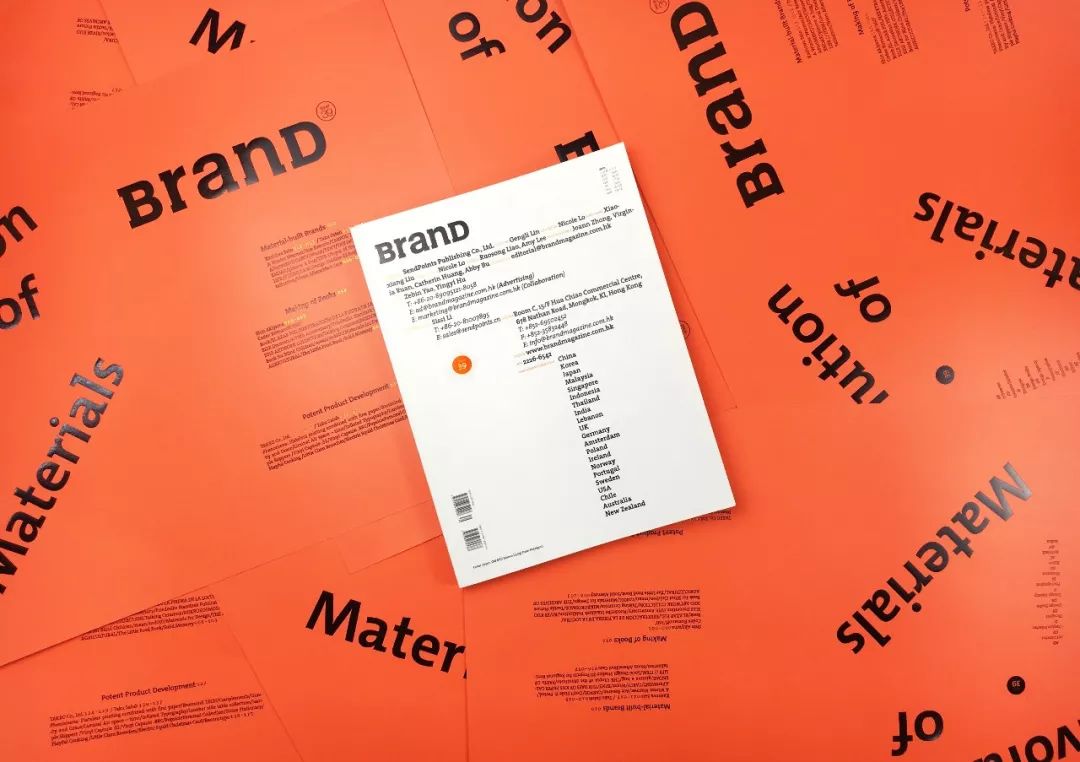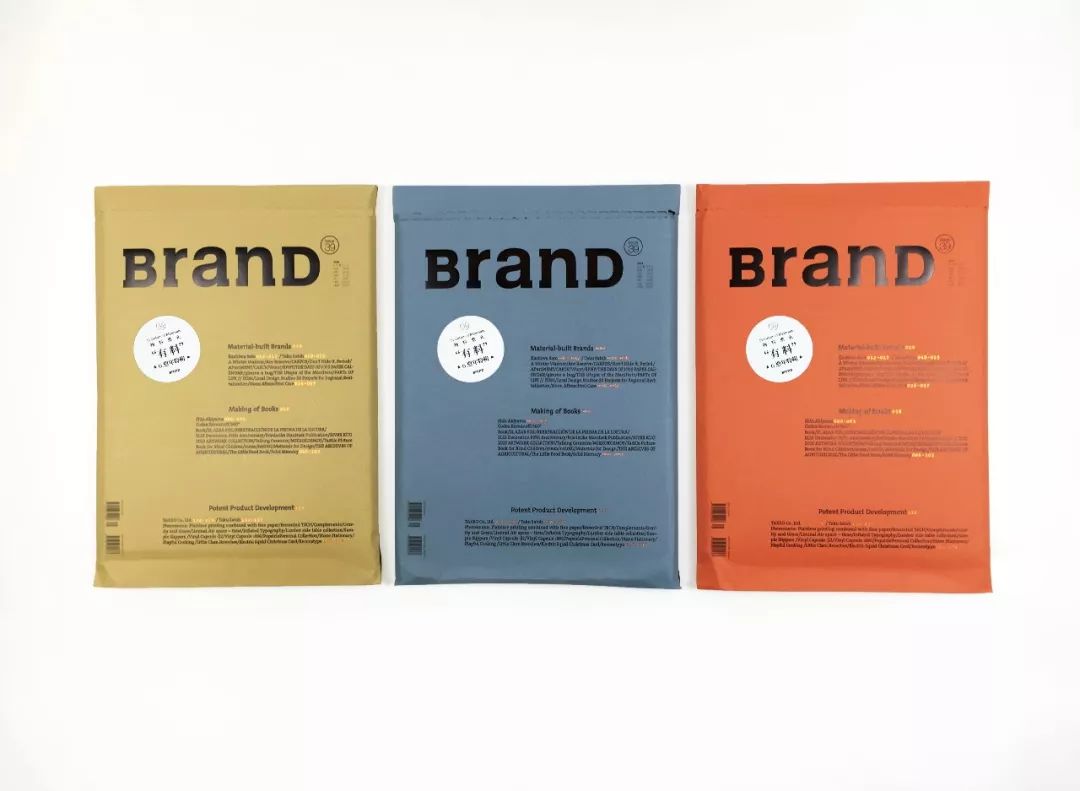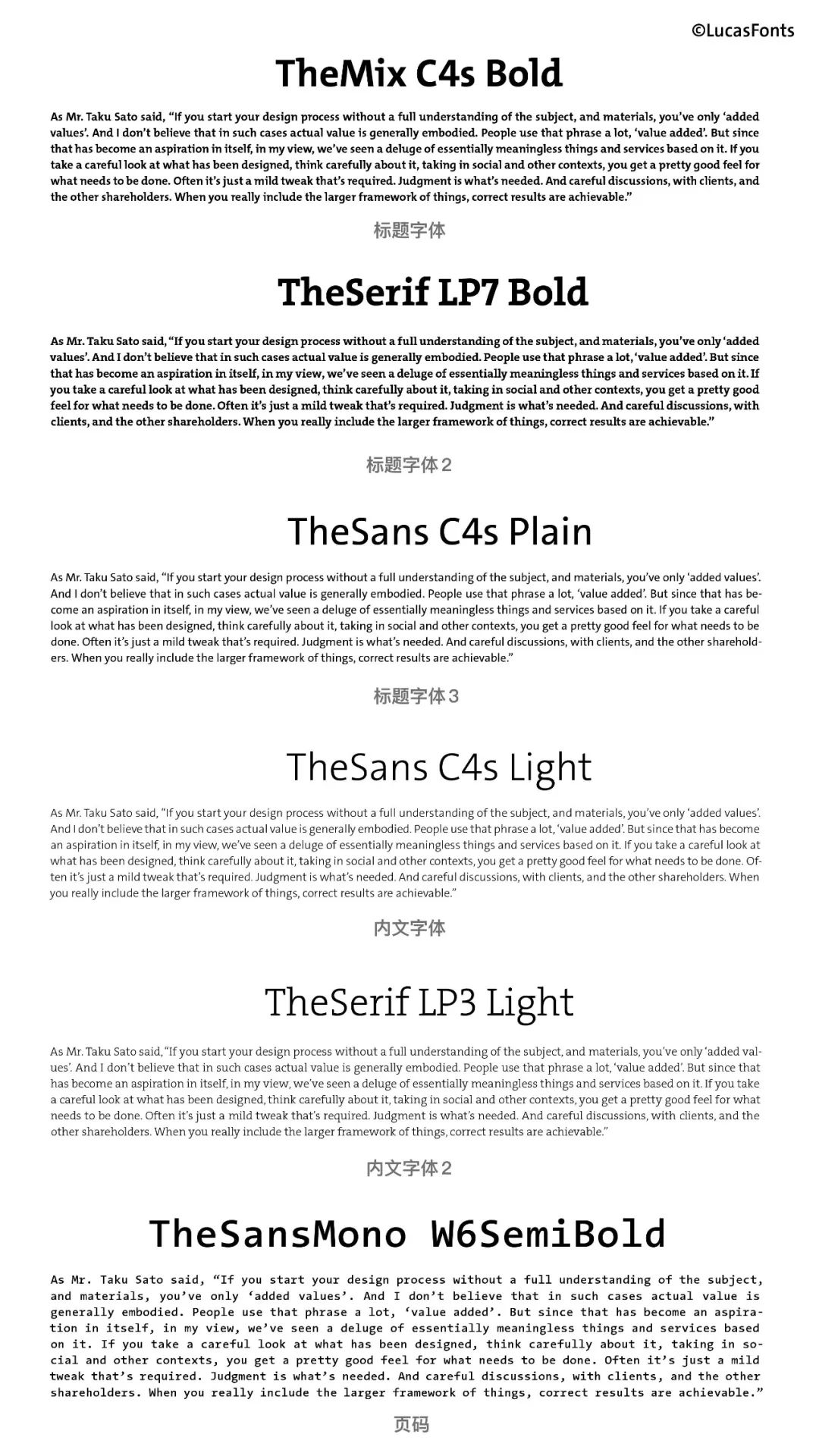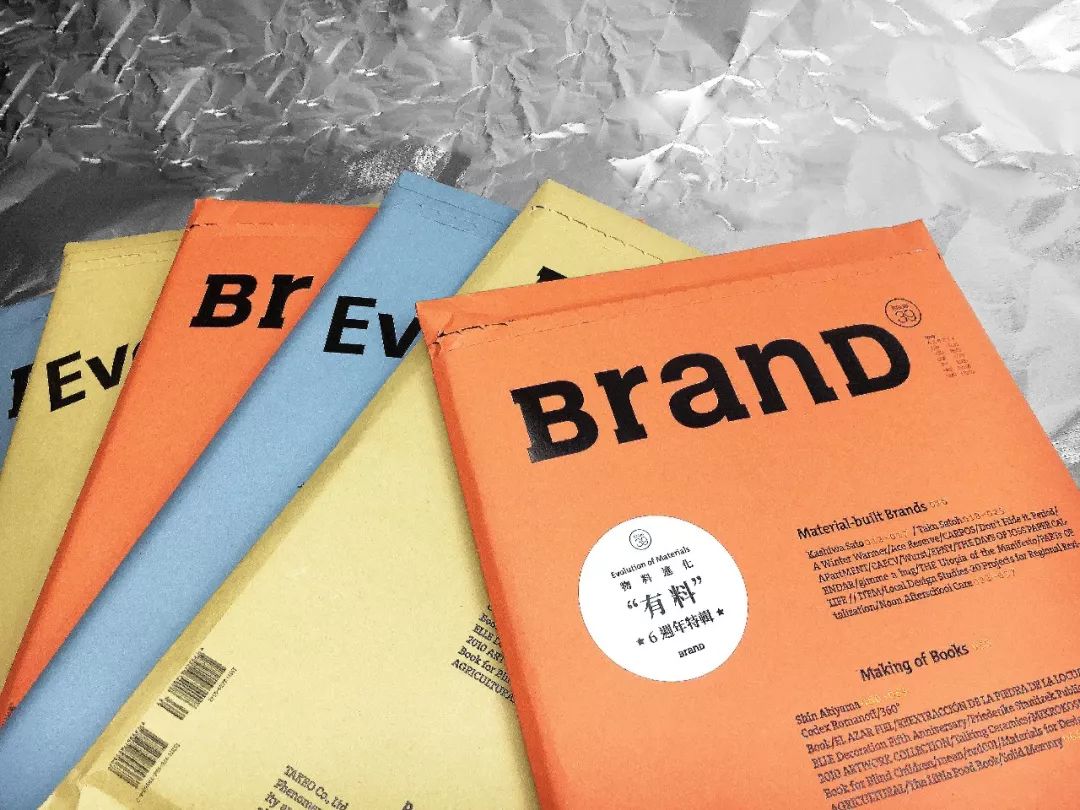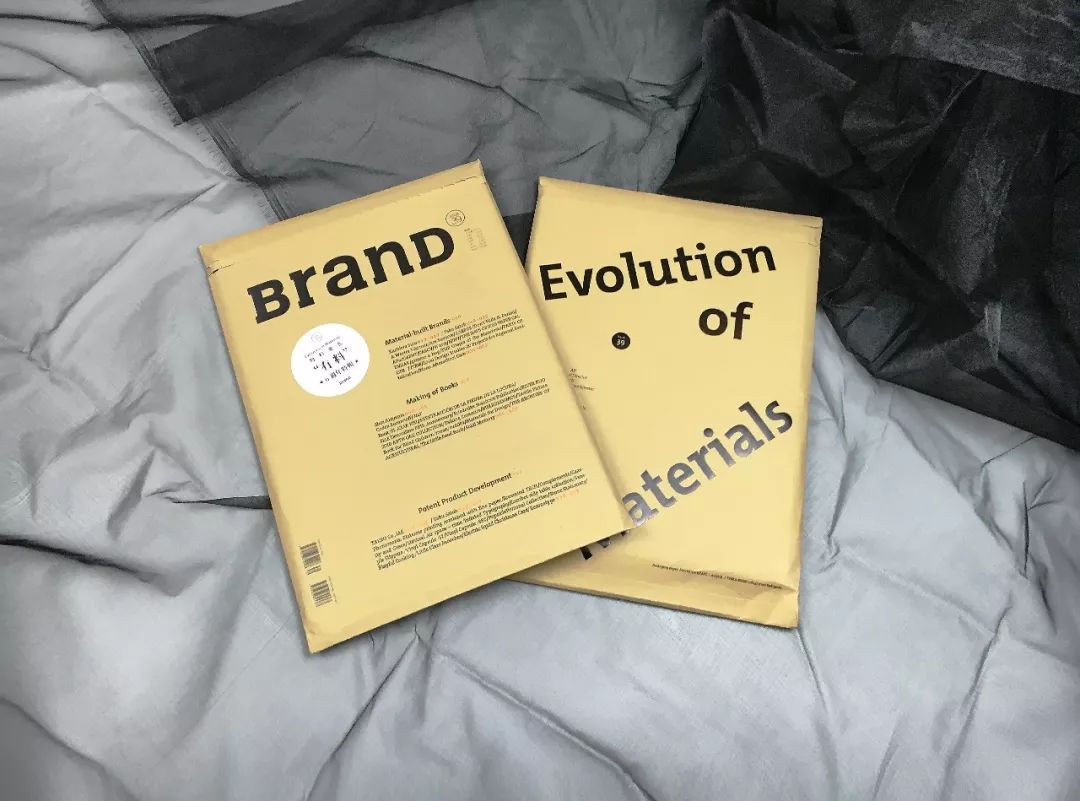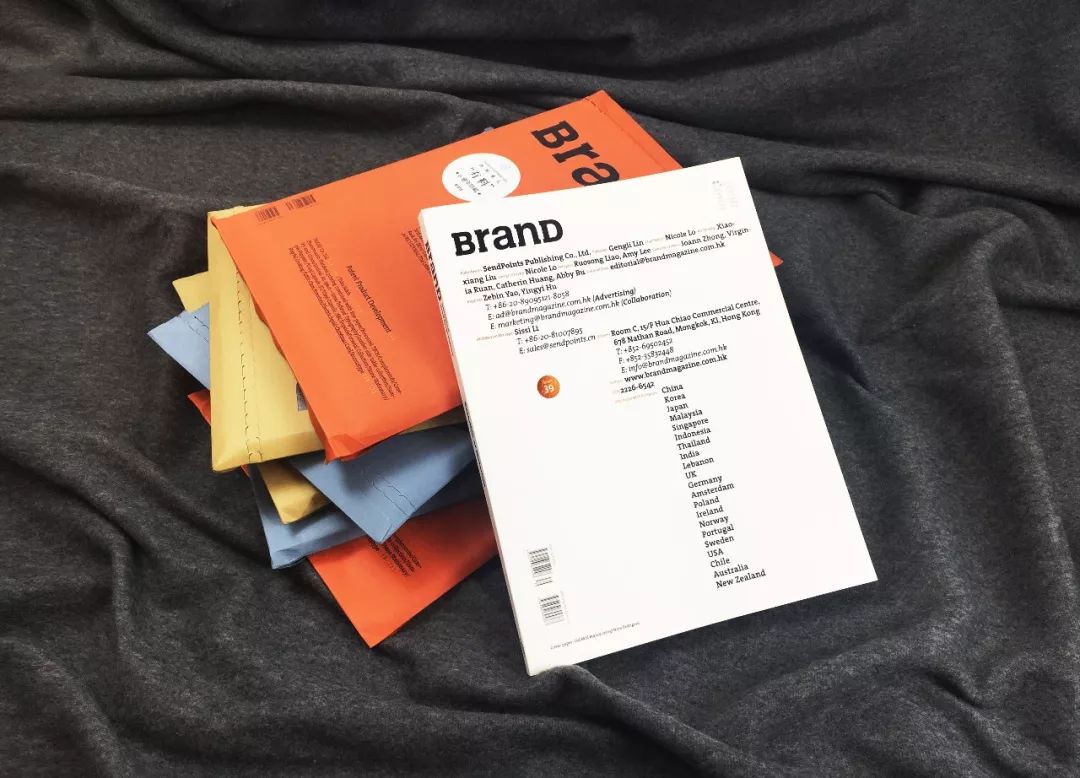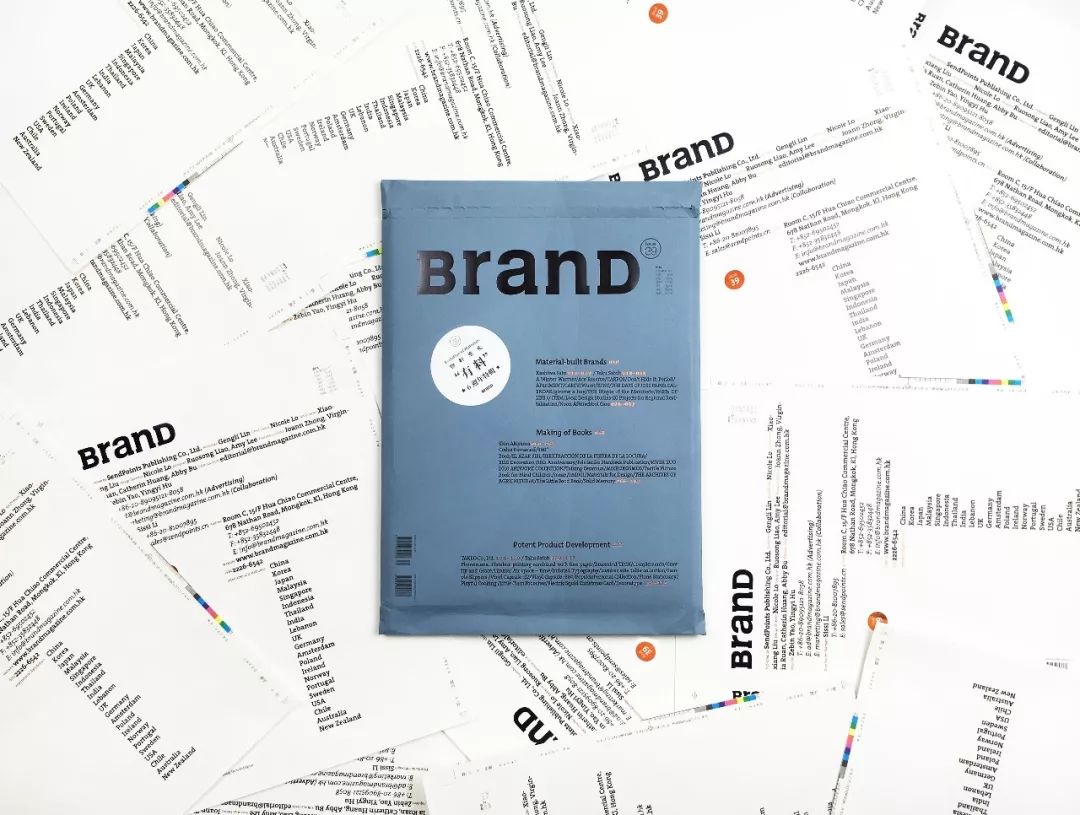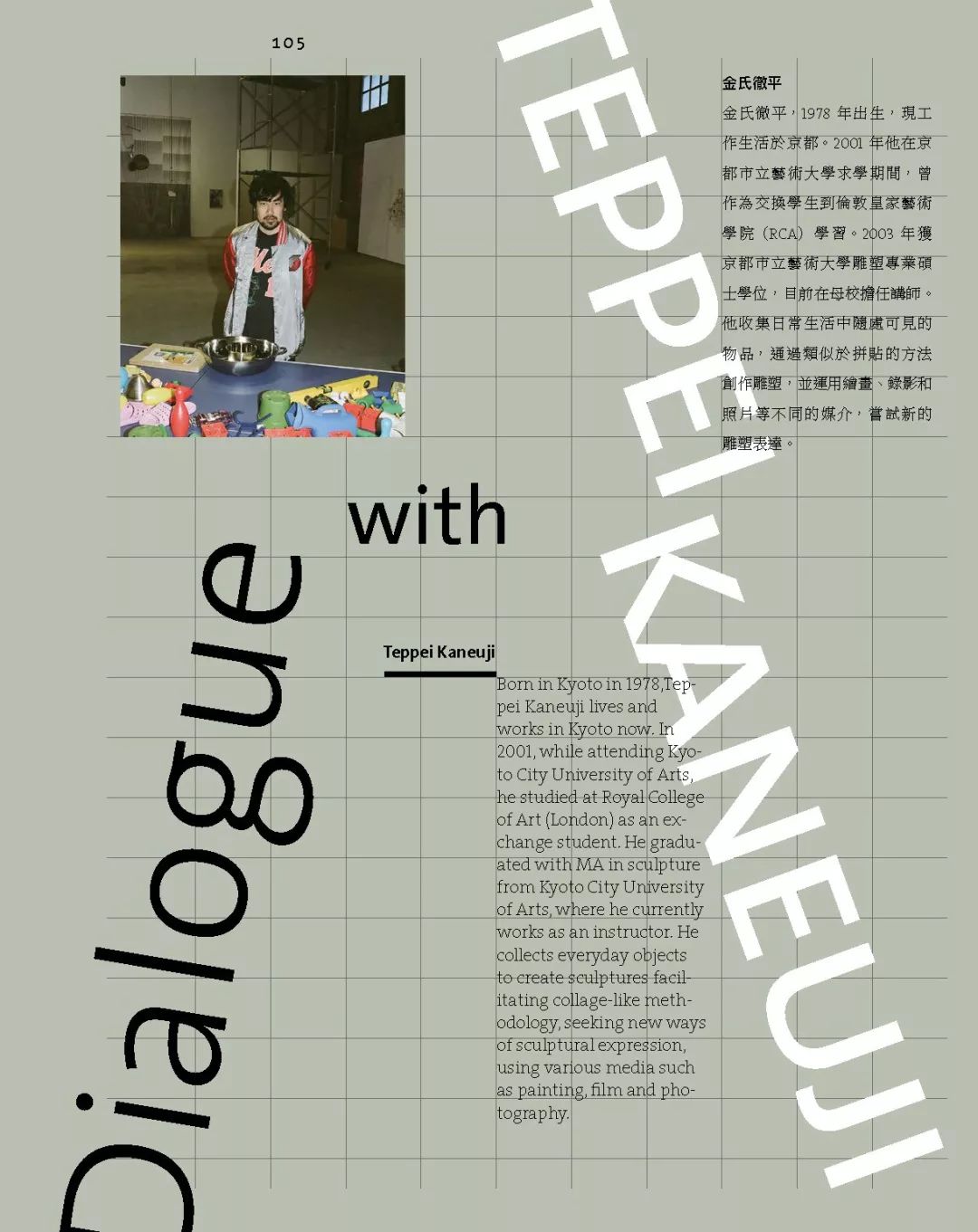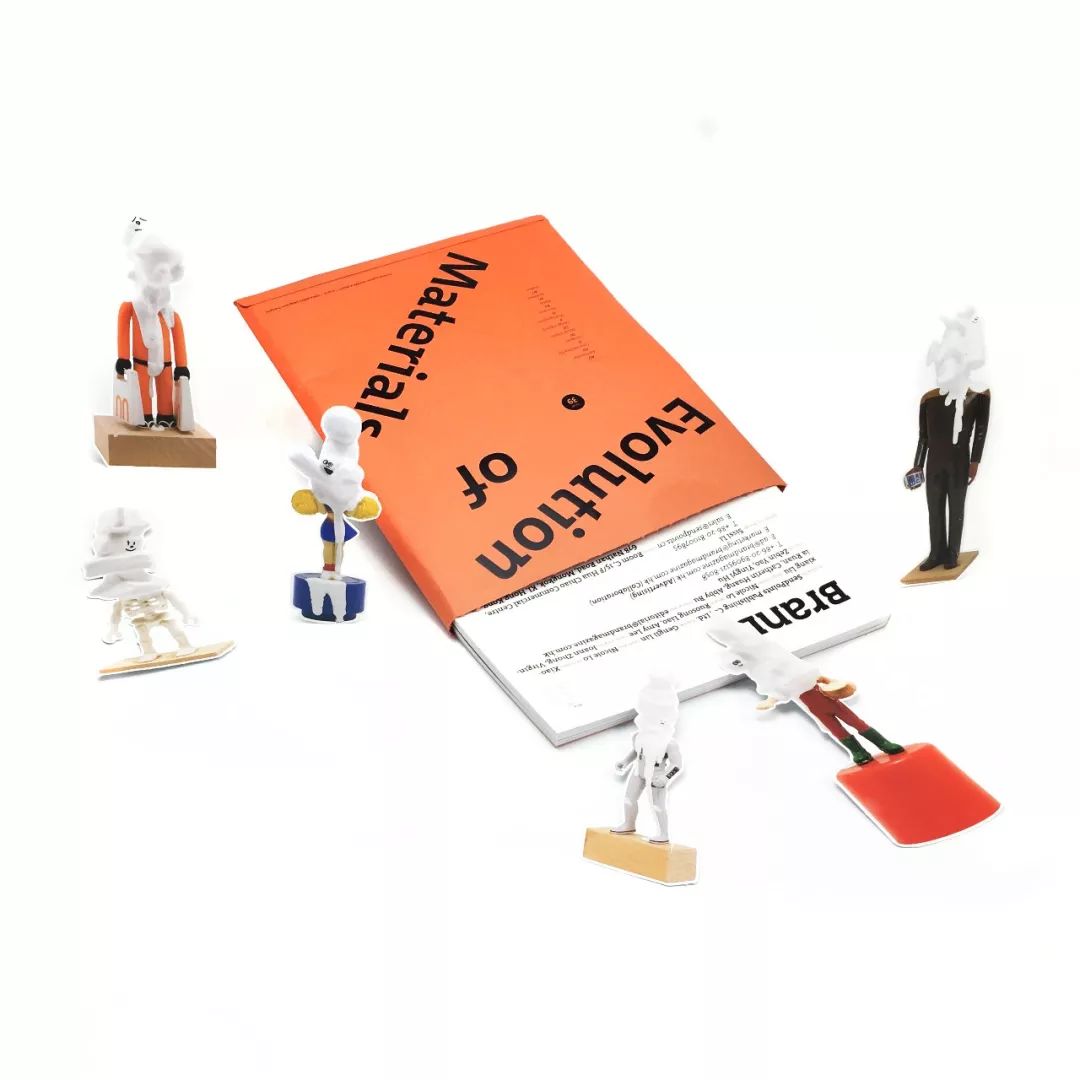
新版式、新字体,BranD杂志背后的AGI成员
BranD6周年-2012~2018年
BranD杂志是一本关于品牌设计的Mook,创刊于2012年,一共分中英文对照版、英文版与欧美版三个版本,每两个月一期,由出版社Sendpoints善本图书有限公司 (www.spbooks.cn)出版,善本创办于2006年,是一家专业的外文图书代理公司,总部设于广州,他们经营图书类别广泛,遍及艺术、设计、文化、生活、旅游、时尚、儿童等等,包括中文繁体版、英文版、日文版、法文版等多个语言版本,合作的出版社有德国TASCHEN和Gestalten、英国Phaidon和Thames & Hudson、美国Random House 和Rizzoli、日本PIE和Seigensha、台湾城邦和读书共和国和三联等出版社等。
BranD是善本其中一本比较固定的杂志,他们还出版一些设计类书籍,例如《今日版式》、《今日色彩》等这些畅销书籍。一个从图书公司出来的,仅仅靠销量吃饭几乎不依赖广告的杂志,坚持了6年,凭什么?如果说他们缺乏媒体属性倒不如说他们发行团队很给力?为什么不能凭内容?别人说出版不行的是因为有人只想在出版界里浑水摸鱼。
一本由中国团队打造的杂志,在全球多个国家不同书店里有售的BranD其实也没有什么了不起,他们认为/不认为自己了不起地,能在浮躁的世界里认认真真地做好内容才算了不起,享受创作内容的过程,转化市场的压力。然而,如果您有买过了BranD,您会发现这本杂志活得越来越漂亮!BranD杂志在2014年出现销售危机,几乎停刊,此时他们决定改版,更换标志,重新规范内容,版式与字体,新团队新主编、新编辑、没有营销概念,4个人把杂志200P填满,2015年第一期主题《品牌正能量》一股拼劲,真的死不了!《品牌正能量》就是要纪念当时的意志力。
“每一次的危机都是一个最好的忠告,别人总跟你说杂志做的很好,但是很少人告诉您还可以怎么做,这都需要自己探索。”BranD主编说,在过去一年里BranD开始尝试跨界合作,挖掘内容的深度,并获得出版社、艺术家们的支持,接下来很多惊喜即将发生。
BranD全新设计:新版式,新字体
BranD6周年邀请了国际平面设计联盟(AGI)成员刘晓翔作为本期艺术总监,负责重新设计版式与字体,刘晓翔认为:“这次改版最大的意义有两点,一是内文字体选择与杂志名的匹配,这样的改版对于一本设计类杂志来说非常重要,另外就是为杂志建立一个可以持续下去的版面网格系统,有了固定的网格系统,便于日后设计师的发挥”。
BranD认为这次改版,不仅仅是版式设计的突破,更是一种碰撞,刘晓翔老师细致深入的观察与设计让我们碰触到更广阔的视野与思想,那些敬畏的,谦虚的,更有活力,更自信…….
换了新字体与版式的BranD除了焕然一新,活力十足,更有一种想要跳起来的律动,刘晓翔老师的版式设计方案更解决了BranD中英文工版印刷的问题,降低了印刷的成本。不管是中文版还是 英文版都酷劲十足!这目前是BranD有史以来制作费用最高的一期了,这是我们对出版的诚意与态度。感谢XXL Studio、LucasFonts、Fedrigoni、P&p及深圳和谐印刷的支持,估计这一期又要抢崩头。
6周年特刊
No.39:"有料”
Ecolution of Materials
物料的意义?
生活在一个物质的时代,人们常常会问:“应该用什么材料好?如何通过材料提高设计的附加值?”我们不难发现人们想通过材料来吸引顾客,有时候这会产生很好的创意,但有时候却不一定,因为当我们滥用材料时会产生一些没有意义的设计,这些都是一种浪费。
正如佐藤卓先生所说:“如果在对项目和材料没有充分理解、认知的情况下就着手开始设计,那么设计师能创造的也就只有‘附加价值’,这样的设计通常体现不出对象的实际价值。 ‘附加价值’是人们常挂在嘴边的一个词。但由于这本身已经成为一种愿望,我觉得我们已经见过太多由此衍生出来、在本质上无意义的东西和服务。如果能仔细看看被设计出来的东西,把它放在社会和其他语境中用心揣摩一下,就能对需要做的事有一个很好的概念,往往是只需要做一点小小的调整就行。真正必要的是判断,以及与客户和其他股东的仔细讨论。当你真正把事物的大框架纳入到思考中时,正确的结果便呼之欲出。”
这一期,讨论材料对我们来说是有挑战的,因为我们不想用很多不同的材料去表现材料的特点与感受,我们更希望我们能给读者提供一个舒适的阅读体验,欣赏设计师们的作品和采访!
BranD No.39 艺术总监:刘晓翔
国际平面设计联盟(AGI)成员、中国出版协会装帧艺术委员会主任委员、刘晓翔工作室(XXL Studio)艺术总监、高等教育出版社编审首席设计。2010年、2012年、2014年三次获得德国莱比锡“世界最美的书”奖、2005年 - 2017年,十七次获得“中国最美的书”奖、2013年获韩国“坡州出版奖•书籍设计奖”(成就奖)、2017金点设计奖、年度最佳设计奖、2018年Tokyo TDC Annual Awards、2018年NYTDC奖项、第97届ADC国际设计大赛铜立方奖。
New Typeface
BranD杂志本次改版在刘晓翔老师的建议下决定采用由LucasFonts设计的字体族:TheSans,TheMix,TheSerif,还包括其各自的斜体(italic),小型大写字母(Caps)和等宽字体(Mono)系列。通过这个大家族从衬线到非衬线的3种字体的过度,混合配搭,达到系统区分3个版块的功能。
中文字体,经过一些筛选,选用Mac自带的PingFang HK和开源字体思源宋体,所有作品案例的倾斜标题均为小型大写字母(Caps),杂志里大量运用了小型大写字母,如页眉,采访人物的名字等,原因是来自BranD的logo设计,logo首尾其实是大写,中间是小写,但logo各字母高度一样且均呈正方形,这和大型小写字母的气质很相像。
章节页英文的倾斜文字不是随机选择的,倾斜在这次的设计是强调的作用,强调关键的词,比如这次分成品牌,书籍和产品,所以只强调对应的英文单词,再根据页面是否美观来调整。
Cover Design
BranD39期的主题:“有料”Evoluyion of Materials,为了更好诠释主题,及感谢版权页里的每一位,感谢过去在这一页里出现过的人,打破常规,选用杂志版权页作为封面。朴实之余却能感受到材料带来的视觉质感。并且选用3种颜色的意大利进口纸张为杂志外包装纸袋,每一种颜色拥有自己的风格并且满满地“有料”。
大咖云集
Kashiwa Sato/佐藤可士和/日本
1965年生于日本东京。毕业于多摩美术大学平面设计系,毕业后进入日本最大的广告公司博报堂任职11年。于2000年成立创意工作室SAMURAI(为“武士”之意)。佐藤可士和曾主导优衣库、本田、7-11、洋马、乐天等大品牌的设计,是全球知名的创意指导,为设计界带来全新的视觉盛宴。
Taku Satoh/佐藤卓/日本
佐藤卓先生生于日本,1979年毕业于东京艺术大学设计专业,1981年又从该校研究生毕业,先就职于电通公司,1984年成立佐藤卓设计事务所。从“NIKKA · 纯麦芽威士忌”商品开发开始,从事过"乐天· 木糖醇口香糖系列"、"明治美味牛奶"、三宅一生副线品牌三宅褶皱等的商品平面设计;还参与过金泽21世纪美术馆、东京国家自然科学博物馆和全国高中棒球锦标赛等的VI设计。
Luc(as) de Groot
丹麦字体设计师Luc(as) de Groot经营管理字体代工厂LucasFonts和柏林的设计工作室FontFabrik。他在全球范围内教授字体设计、开展讲座和工坊。Lucas de Groot闻名于他设计的字体家族——TheSans、 TheSerif、TheMix和TheAntiqua,但他涉猎的范围更为广泛。他与其团队一起为全球公司设计企业字体和报纸的定制字体。
Teppei Kaneuji/金氏彻平/日本
金氏彻平金氏彻平,1978 年出生,现工作生活于京都。2001 年他在京都市立艺术大学求学期间,曾作为交换学生到伦敦皇家艺术学院(RCA)学习。2003 年获京都市立艺术大学雕塑专业硕士学位,目前在母校担任讲师。他收集日常生活中随处可见的物品,通过类似于拼贴的方法创作雕塑,并运用绘画、录像和照片等不同的媒介,尝试新的雕塑表达。